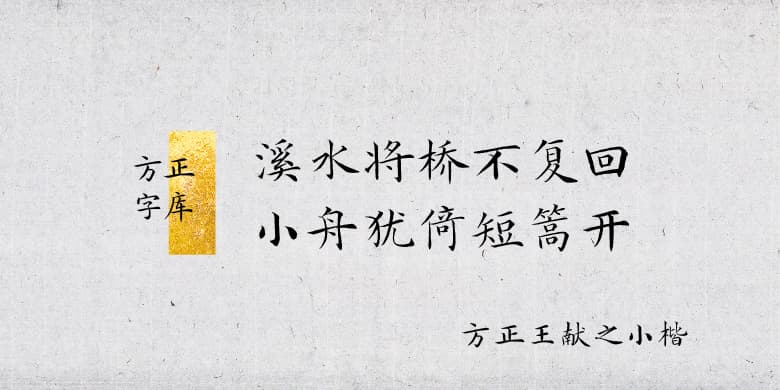
方正王献之小楷
品牌:方正字库中华精品字库设计师:夏云发行时间:2021字库编码:大陆简体(GB2312-80)分类:常规书写·毛笔字体属性:精品字
关于王献之
王献之(344~386年),东晋书法家。字子敬,琅玡临沂(今山东省临沂市)人。王献之精习书法,与其父王羲之并称“二王”,又有“小圣”之称。他少负盛名,才华过人,前人评论王献之的书法为“丹穴凰舞,清泉龙跃。精密渊巧,出于神智。”代表作品有《中秋帖》、《鸭头丸帖》《洛神赋十三行》等。
字体特征:
以王献之《洛神赋十三行》为临创开发依据;体势秀逸、笔致洒脱、虚和简静、灵秀流美;结体宽敞舒展;线条遒劲有力,神采飞扬。
应用场景:
临创者:夏云
整理/设计:王军芳、邹诗琪、史通通、刘婷婷
审稿专家:刘洪彪、李有来、朱培尔、虞晓勇、邵佩英、张志庆、仇寅